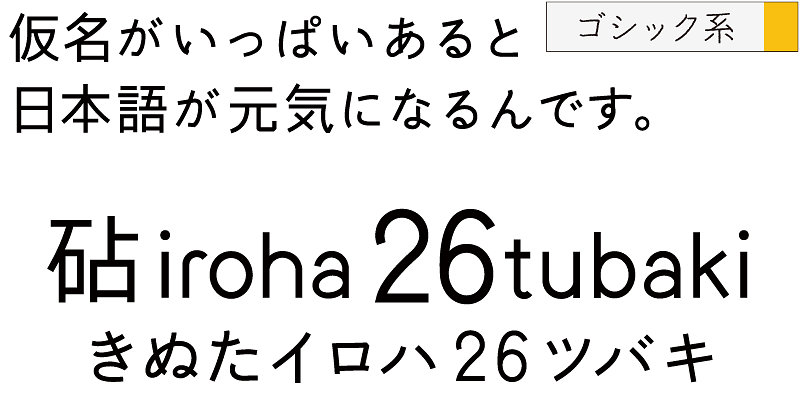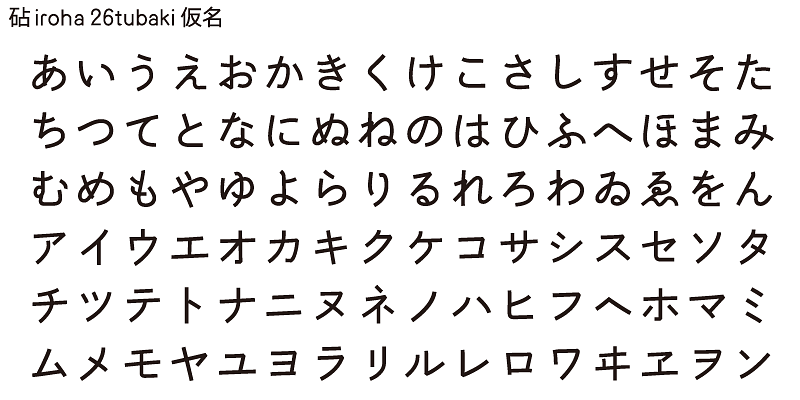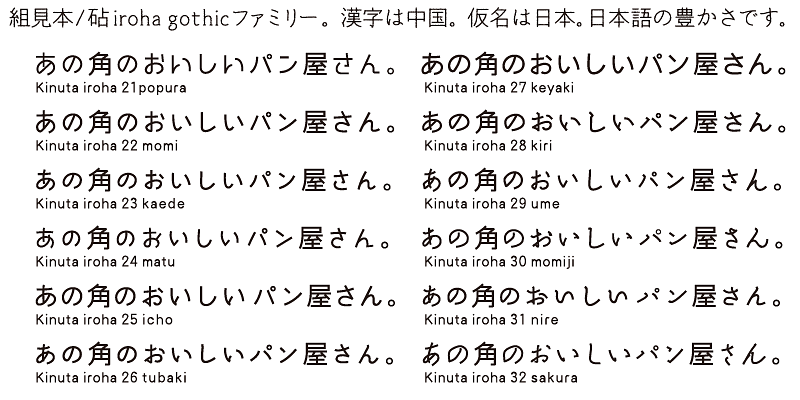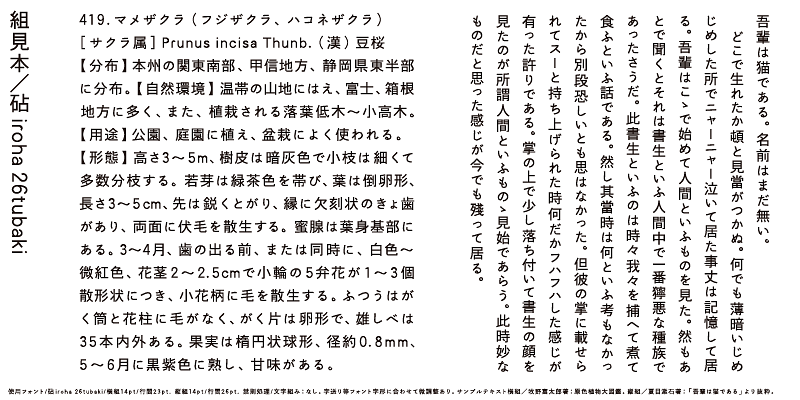
Iroha 26tsubaki es un tipo de letra atemporal y versátil con un sabor a escritura a mano con pincel que aporta madurez al tipo de letra. La combinación de Iroha 26tsubaki con un diseño de kanji de estilo moderno crea una sinergia armoniosa.
Todas las variantes de Iroha comparten los mismos caracteres ideográficos (kanji). Los caracteres kanji de Iroha están diseñados con trazos lineales y estructuras simples. Hay 12 variantes de kana.
Una característica del japonés es que tiene caracteres silábicos llamados kana. Los caracteres kana se inventaron para representar sonidos en japonés y traducir textos importados de China. Los caracteres kana son necesarios para crear palabras y expresiones japonesas a partir de caracteres ideográficos kanji, que son caracteres chinos. Si bien puede haber ambigüedades, estas palabras y expresiones exhiben la cercanía y amabilidad de las personas que viven en la pequeña y densamente poblada tierra de Japón.
Kinuta Font Factory cree que los caracteres kana son el origen de las palabras escritas en japonés, y que mejorar los caracteres kana hará que el texto japonés sea más atractivo. En promedio, el 60 % del texto japonés se compone de caracteres kana; cambiar la forma de estos caracteres cambia la apariencia visual del texto. Las posibilidades de expresión tipográfica utilizando caracteres kana sencillos, dinámicos y curvilíneos son enormes, y la riqueza del texto japonés depende de ellos en gran medida. Esta es la razón por la que Kinuta Font Factory ofrece muchas variaciones de tipos de letra kana.